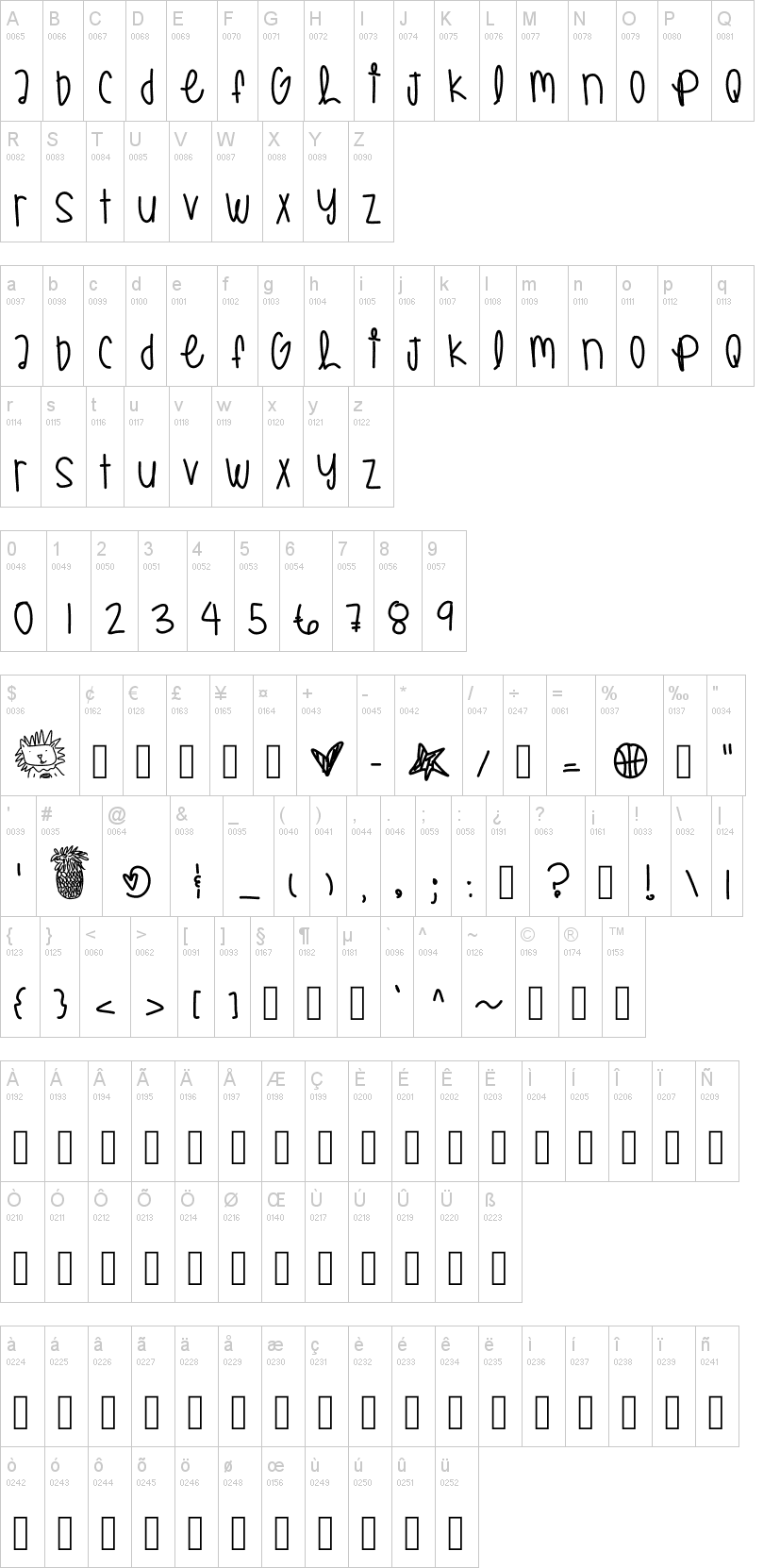
All Star Game Yay
All Star Game Yay字体是一款手写风格的字体,它有着活泼而有趣的外观,适合用于创造有趣的文字效果。它具有粗细变化,可以用于添加视觉效果,也可以用于演示或海报等。这款字体的设计灵感来自于篮球比赛中的明星球员,具有活力和活力,可以为您的项目添加一丝活力。
All Star Game Yay是一款非常不错的手写艺术字体,具有很好的视觉感,适合于文化类的宣传设计、商业类品牌的广告和产品包装设计以及个性化文字排版等较多场景。
All Star Game Yay字符映射图